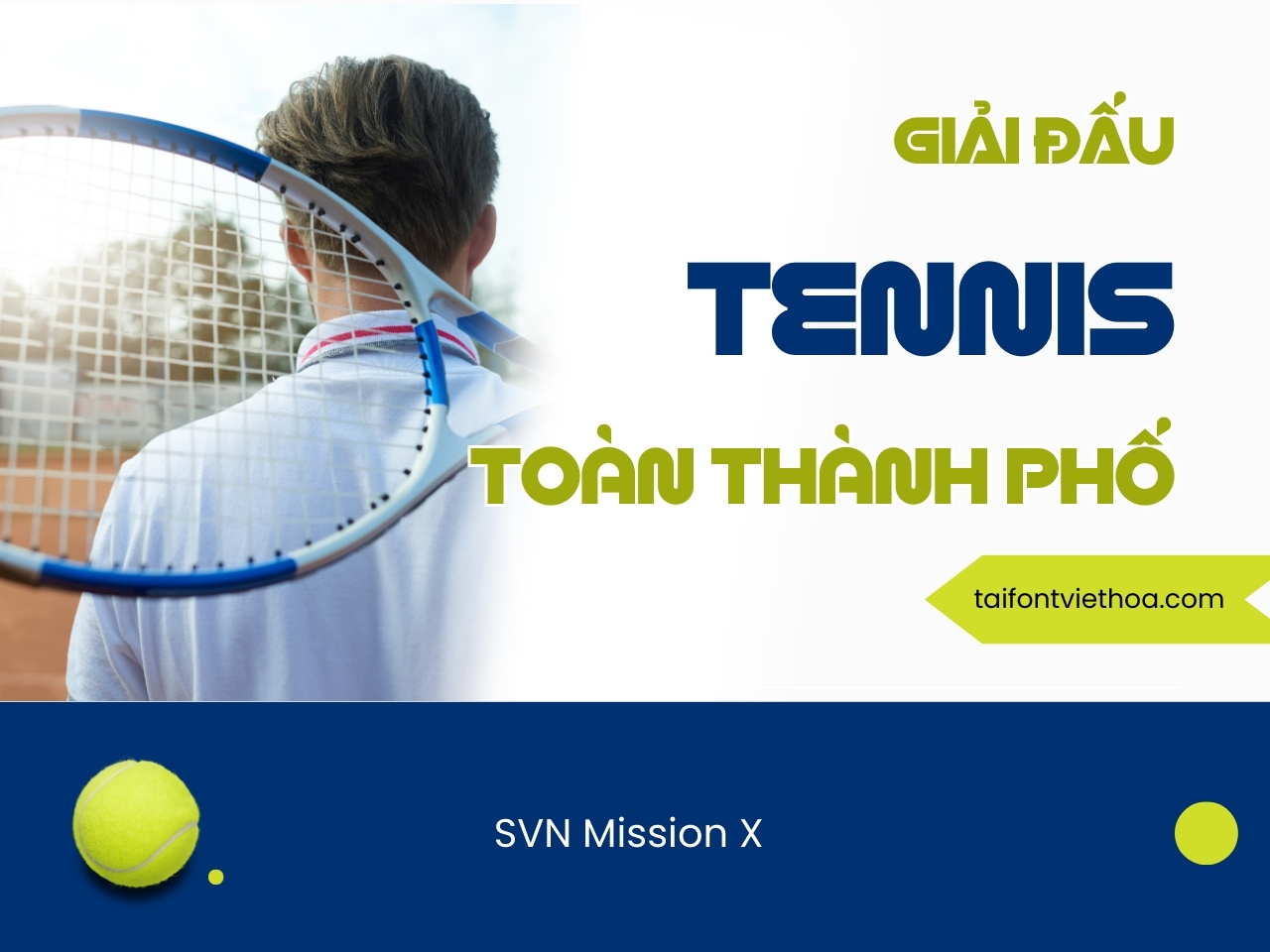
Font việt hóa SVN Mission X
Font việt hóa SVN Mission X font thể thao
Tác giả Font: Lunara Audrey
Giới thiệu về font SVN Mission X – Kiểu chữ sans-serif hiện đại, mạnh mẽ và cá tính
SVN Mission X là phiên bản Việt hóa của font Mission X – một kiểu chữ sans-serif mang phong cách hiện đại, đậm nét và cá tính. Font được thiết kế nhằm mang lại sự năng động, trẻ trung và nổi bật, phù hợp với các dự án thiết kế thương hiệu, quảng cáo và truyền thông kỹ thuật số.
Thiết kế đậm nét, sắc cạnh – Ứng dụng đa dạng trong thương hiệu và quảng cáo
SVN Mission X sở hữu các nét chữ dày, rõ ràng và góc cạnh, tạo cảm giác chắc chắn, cá tính và năng động. Font có cấu trúc sans-serif không chân, dễ đọc và phù hợp cho các tiêu đề, banner, logo hoặc poster cần sự thu hút và ấn tượng mạnh mẽ. Phong cách thiết kế của Mission X rất thích hợp với các dự án thể thao, công nghệ, quảng cáo và các thương hiệu trẻ trung, sáng tạo.
Ứng dụng lý tưởng: thiết kế logo, poster quảng cáo, banner sự kiện, nhận diện thương hiệu thể thao, website công nghệ, sản phẩm âm nhạc và các dự án marketing sáng tạo. Ngành nghề phù hợp: thể thao, giải trí, công nghệ, quảng cáo, thương mại điện tử và startup sáng tạo.